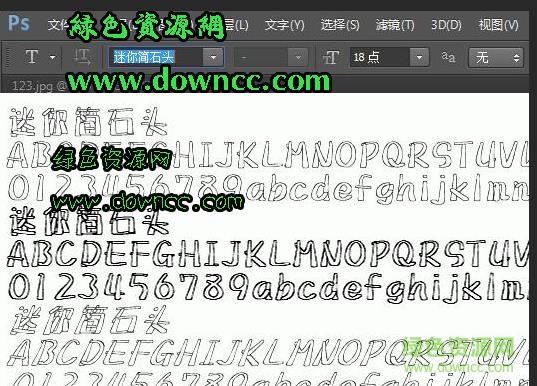
迷你簡石頭字體
迷你簡石頭字體看起來就如一個個的石頭堆疊在一起組成的字體,給你十分不錯的視覺效果是用戶在各類文件編輯中時尚選擇到的有趣文字樣式,為你代帶來優(yōu)秀的顯示風(fēng)格,需要的朋友就請來綠色資源網(wǎng)下載使用吧!
迷你簡石頭字體看起來有種凌亂的美,字體中空,像字體名字一樣,也因其獨特,常被用戶用于各類設(shè)計行業(yè),是款不錯的字體。